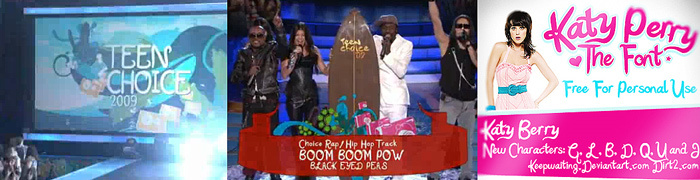
Katy Berry autorstwa Dirt2.com to darmowy krój pędzelkowy o szerokich, przypominających tusz pociągnięciach i swobodnym, odręcznym pochyleniu. Zaokrąglone połączenia, ostre zawijasy i długie, zamaszyste ogonki nadają literom żywą sylwetkę, bliższą szybkiemu szyldownictwu niż starannej kaligrafii.
Piekarnia, kawiarnia lub marka żywności rzemieślniczej mogłaby go użyć, aby sugerować osobiste etykietowanie i świeże przygotowanie. Nadaje się również na szyldy targowe i swobodne plakatowanie imprez. Na ilustrowanej etykiecie lub godle sklepu pętle mogą pełnić funkcję wstążek, linii lukru lub ręcznie rysowanych ramek.